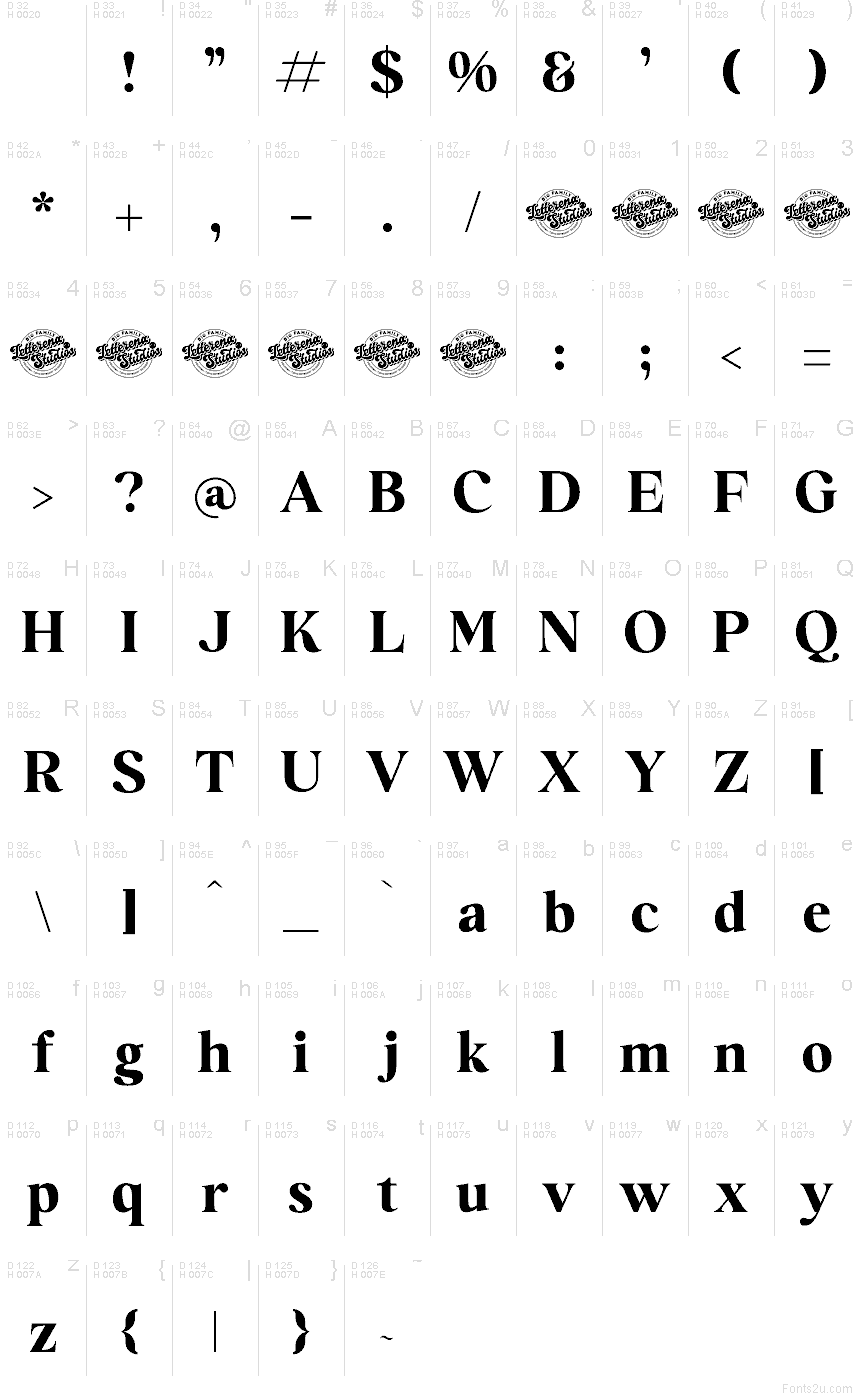
Brilyan Rogale von Letterena Studios ist eine kostenlose Serifenschrift mit hohem Kontrast und einer modischen Editorial-Ästhetik. Die Buchstaben verbinden klare, skulpturale Striche mit weichen, abgerundeten Übergängen und tropfenartigen Punkten, wodurch die Schrift eher elegant als streng wirkt.
Sie eignet sich hervorragend für Magazin-Titel, Beauty-Verpackungen, Boutique-Branding, Buchtitel und kurze Plakat-Überschriften, bei denen ein wenig Kontrast den Unterschied macht. Als kostenlose Schrift ist sie zudem ideal für Social-Media-Grafiken und Titelkarten, besonders wenn Sie eine raffinierte Serifenschrift suchen, die in Buchstaben wie r, i und y eine leicht verspielte Dynamik besitzt.